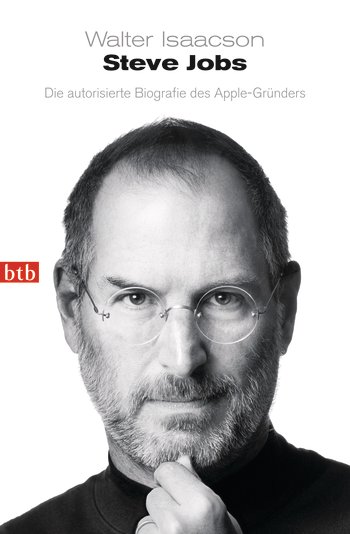
Aber glaubt bitte nicht, dass an der Typografie des Titels etwas geändert wurde. Wir hatten hier im Fontblog ausführlich darüber diskutiert (Warum Steve Jobs ein Kontrollfreak war), wieso die Originalausgabe so aussieht wie sie aussieht, und warum der deutsche Titel lieblos (oder kenntnislos) lokalisiert wurde. Der streitbare Werber Bernd Kreutz in Düsseldorf stieß auf seinem Reklamehimmel kurz darauf ins gleiche Horn: Die Leichenschänder von Bertelsmann. Wir wissen auch aus sicherer Quelle, dass Bertelsmann damals mitlas. Bewegt hat’s nicht viel. Das Cover der Taschbuchversion von btb ziert schlicht eine verkleinerte Version des Dreizeilers vom Herbst letzten Jahres, allein das Foto wurde entzerrt.
Steve-Jobs-Bio seit heute als Taschenbuch